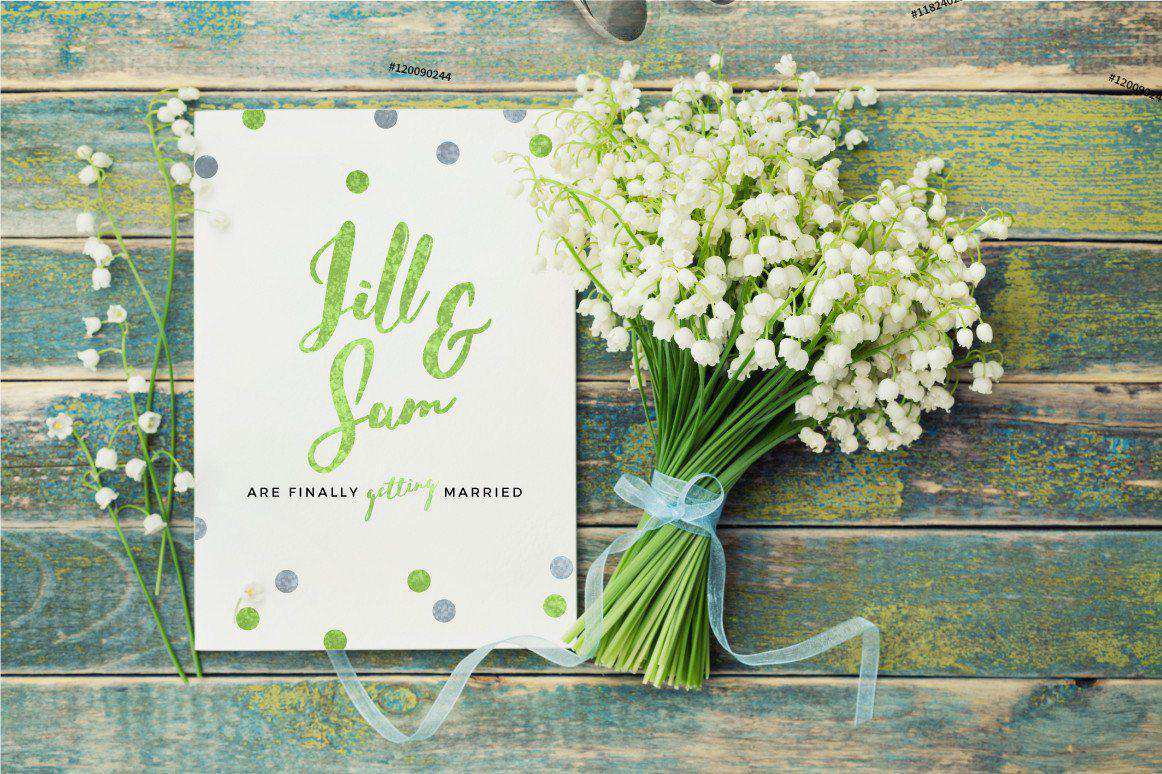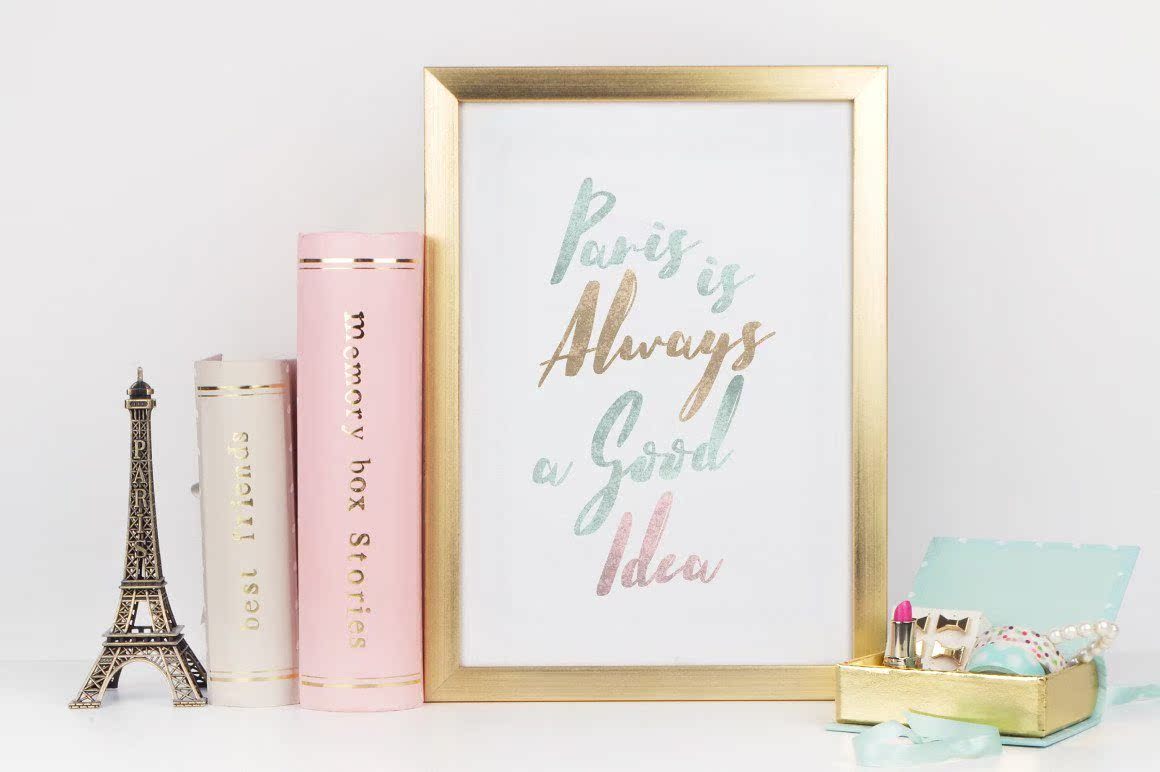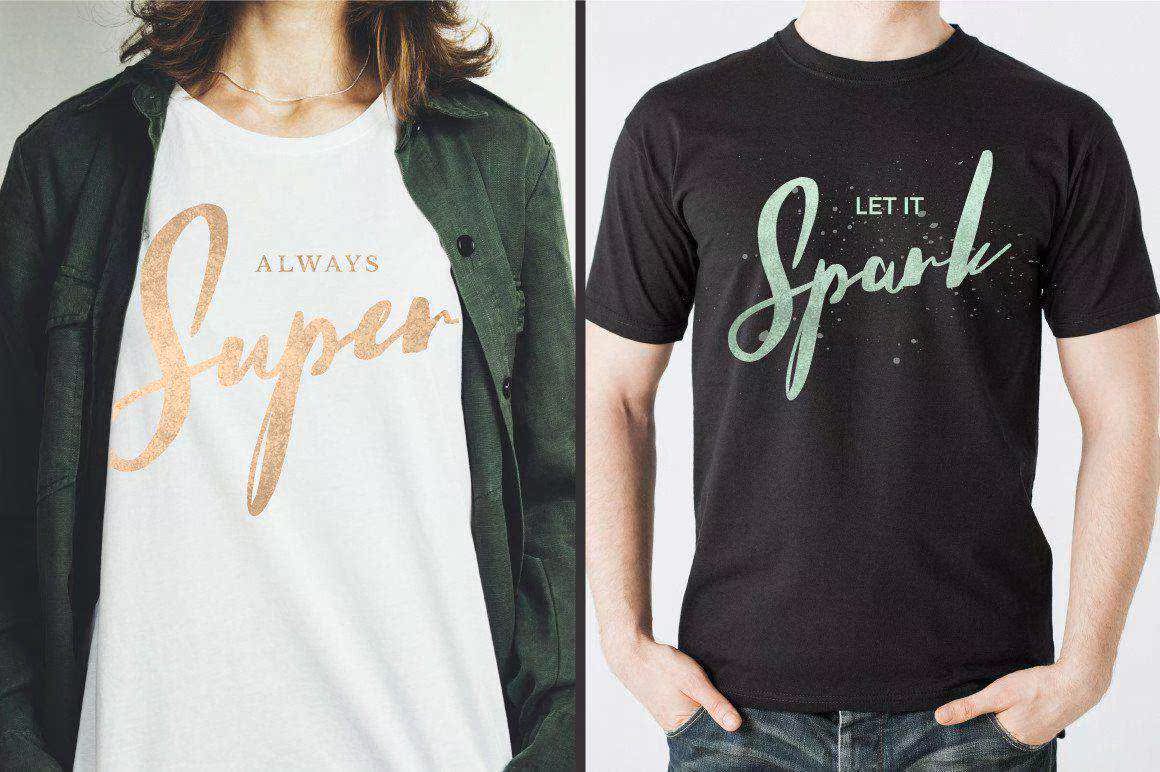
介绍:手工制作的新字体,HelloStockholm!这是一款完美无瑕的现代冲压式脚本字体,由Candinavian和极简主义设计,具有独特的驱动力。设计像专业人士一样,具有这种类型的面,非常适合您的婚礼、街景、Instagramposts、t恤设计、品牌,更重要的是,这种字体深受现代键盘的启发,您可以将Beautifulscript与一个完美匹配的Ansser字体相结合。包括大写字母和小写字母,作为另一种语言支持。这两种字体都包含OTFandtTF文件类型。介绍:提供手工字体,HelloStockholm!这是一款完美无瑕的现代冲压式脚本字体,由Candinavian和极简主义设计,具有独特的驱动力。设计像专业人士一样,具有这种类型的面,非常适合您的婚礼、街景、Instagramposts、t恤设计、品牌,更重要的是,这种字体深受现代键盘的启发,在现代键盘上,您可以将eAutifulscript与一个完全匹配的ansserifont相结合。包括大写字母和小写字母,也可以与多语言支持相结合。这两种字体都包含otfandtfiletype。